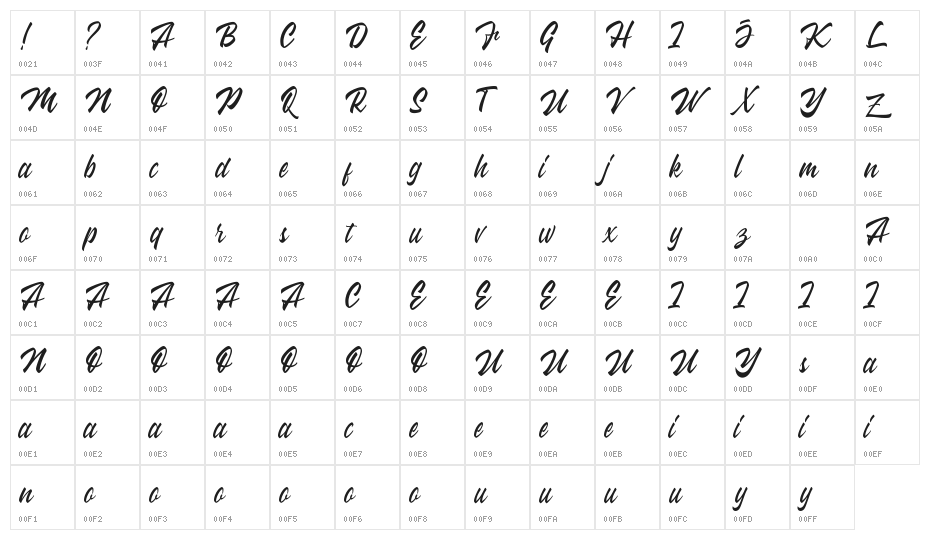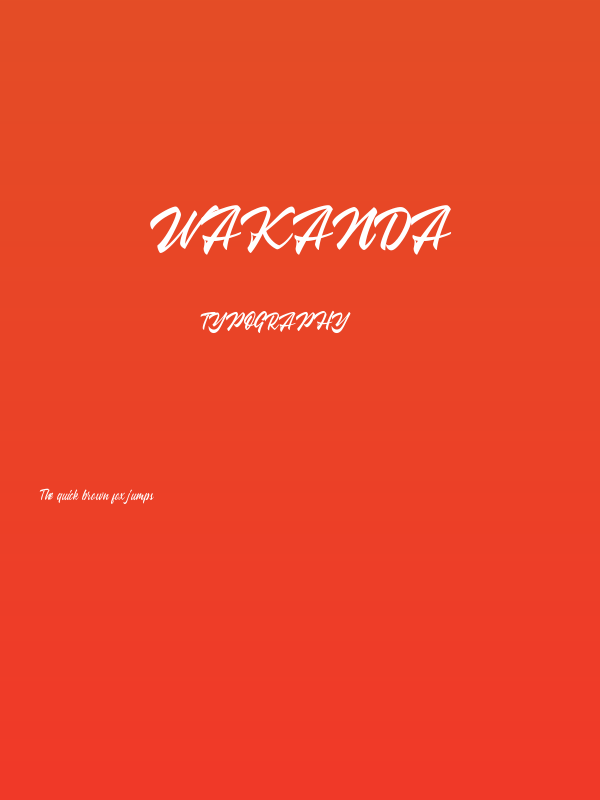
Wakanda Font
✎ Calligraphic
| Kategorien | Calligraphic |
| Anwendungsfall | Logos, Headlines, Invitations |
| Vorgeschlagene Projekte | Ideal for wedding invitations, branding projects, logo design, and elegant packaging. |